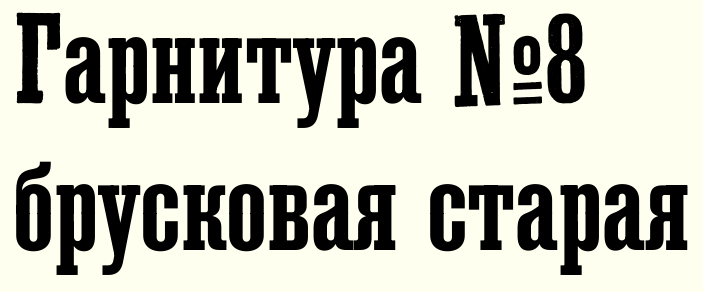
Шрифт Египетский полужирный/DXEgyptianFett
В работе шрифт Египетский полужирный/DXEgyptianFett, также известный как Гарнитура №8 Брусковая старая, кириллическая версия шрифта Egyptienne Schmale, ок.1870